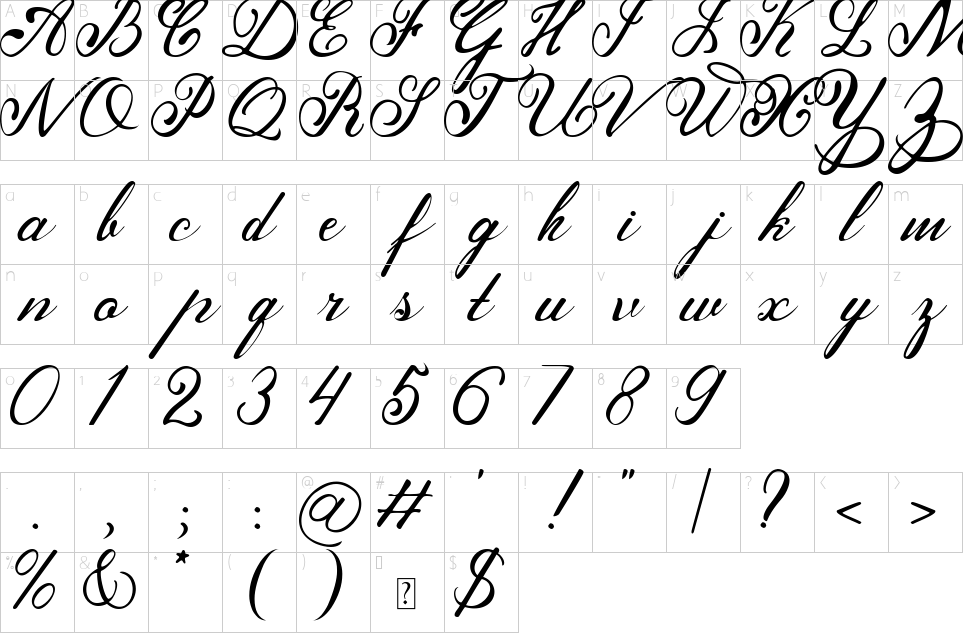
A Murisa Barbara é uma fonte elegante e atraente que traz ao seu projeto um ar sofisticado e moderno. Desenvolvida pela designer Lili Sadili, ela é uma criação que combina perfeitamente tanto no design gráfico quanto em projetos digitais. Com seu design cuidadosamente elaborado, essa fonte é ideal para qualquer aplicação que precise de um toque de elegância e sofisticação. Sua versão gratuita é uma ótima opção para designers e ilustradores que procuram uma fonte atraente e versátil para suas criações. Com ela, você pode expressar a personalidade de seus projetos de maneira única e sofisticada. Esta fonte tem sido baixada por outros designers mais de 3.659 vezes, o que prova sua popularidade e qualidade. Se você está procurando por uma fonte de qualidade e beleza, Murisa Barbara é uma escolha perfeita.